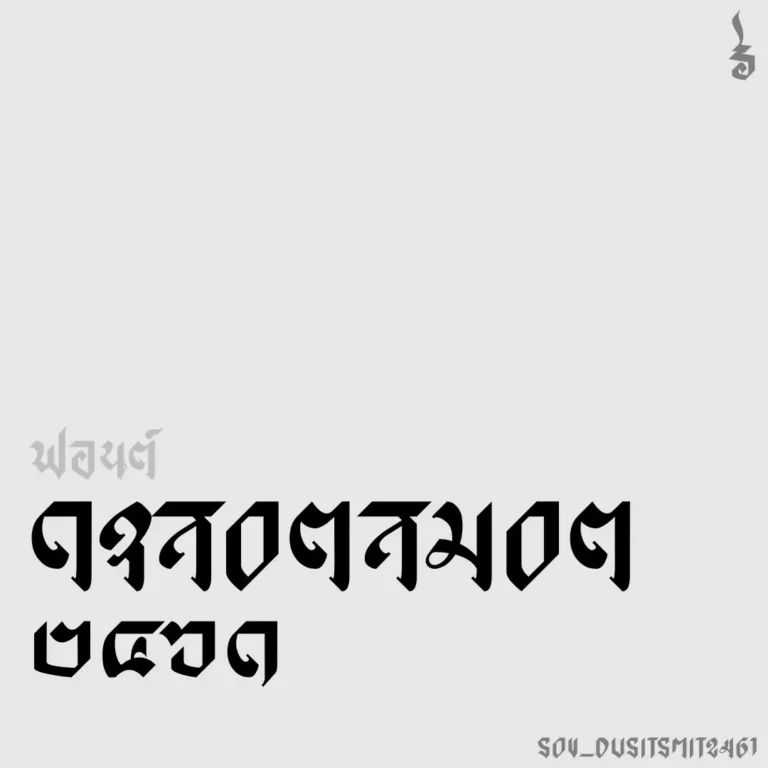
ได้แนวคิดมาจากลายมือสวยๆ บนรถสองแถว (ส.สุขุมวิทการช่าง) จึงหัดเขียนปากกาหัวตัด จนได้แบบเป็นของตัวเอง คือไม่ลากเส้นตรง และอักษรตัวแรกจะเป็นตัวใหญ่กว่าตัวอื่น
เตโช (SOV_tejo)